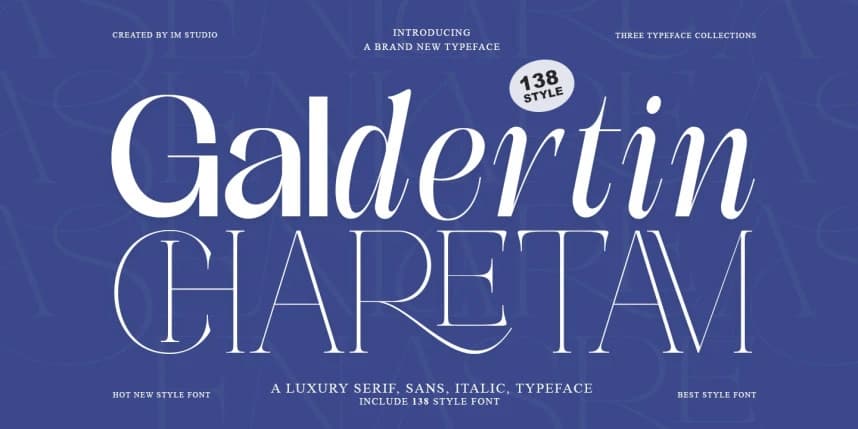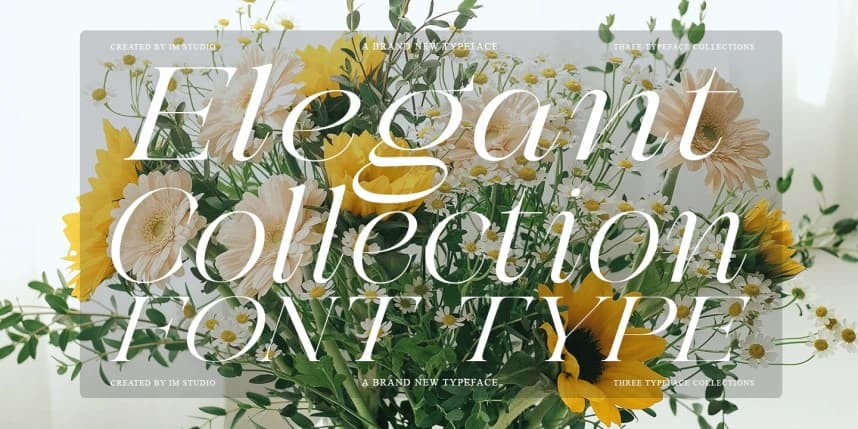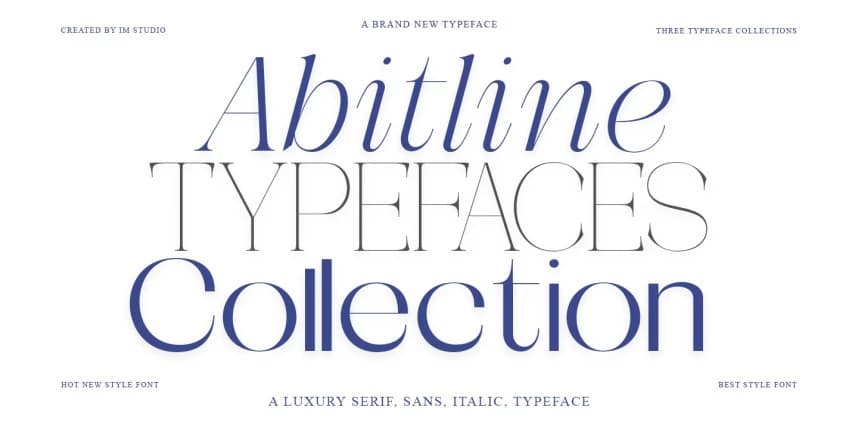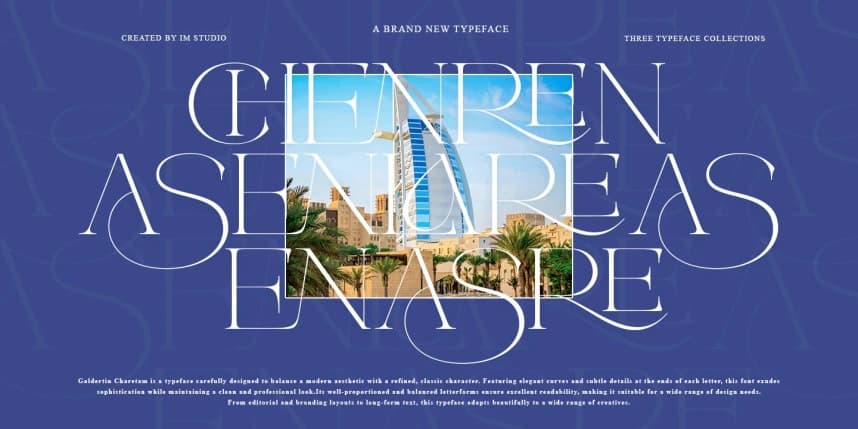
Galdertin Charetam Font
Galdertin Charetam Font: Tipografik Zarafetin Nihai Tezahürü. Galdertin Charetam sadece bir yazı tipi değildir; kesin bir stil ifadesidir. IM Studio tarafından tasarlanan bu gösteri yazı tipi, klasik mirasın görkünü ile c harfinin keskin kenarı arasındaki sofistike bir köprü görevi görür.
Galdertin Charetam Fontu: Tipografik Zarafetin Nihai Tezahürü. Galdertin Charetam sadece bir yazı tipi değildir; bu, belirleyici bir stil ifadesidir. IM Studio tarafından tasarlanmıştır; bu gösteri yazı tipi, klasik mirasın ihtişamı ile çağdaş estetiğin keskin uçları arasında zarif bir köprü kurar.